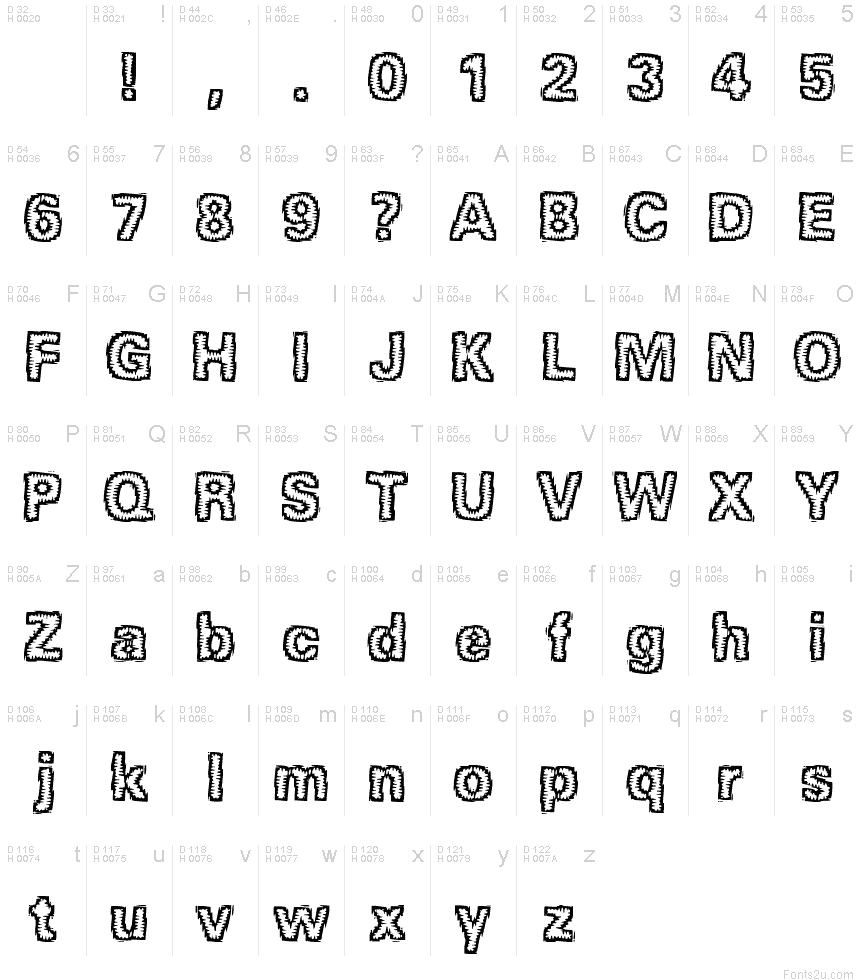
Jagged di Ænigma Fonts è un carattere display gratuito dallo stile eroso, come se fosse stato ritagliato nella carta con un coltello smussato. Le lettere, spesse e squadrate, sono lacerate da vuoti bianchi e contorni irregolari, donando a ogni parola un'energia frenetica e vibrante. Ha un aspetto rumoroso, ruvido al tatto e leggermente folle: l'ideale quando cerchi un testo che sembri essere sopravvissuto a malapena alla stampa.
Con Jagged, i tuoi titoli attirano subito l'attenzione, rendendola perfetta per locandine horror, volantini di Halloween, grafica per concerti punk o metal, menu di videogiochi, miniature di YouTube e sticker dal design audace. Questo font gratuito dà il meglio di sé in grande e in grassetto; abbinalo a un sans serif pulito e neutro per i corpi minori, così il caos di Jagged potrà essere protagonista senza soffocare il resto del layout.